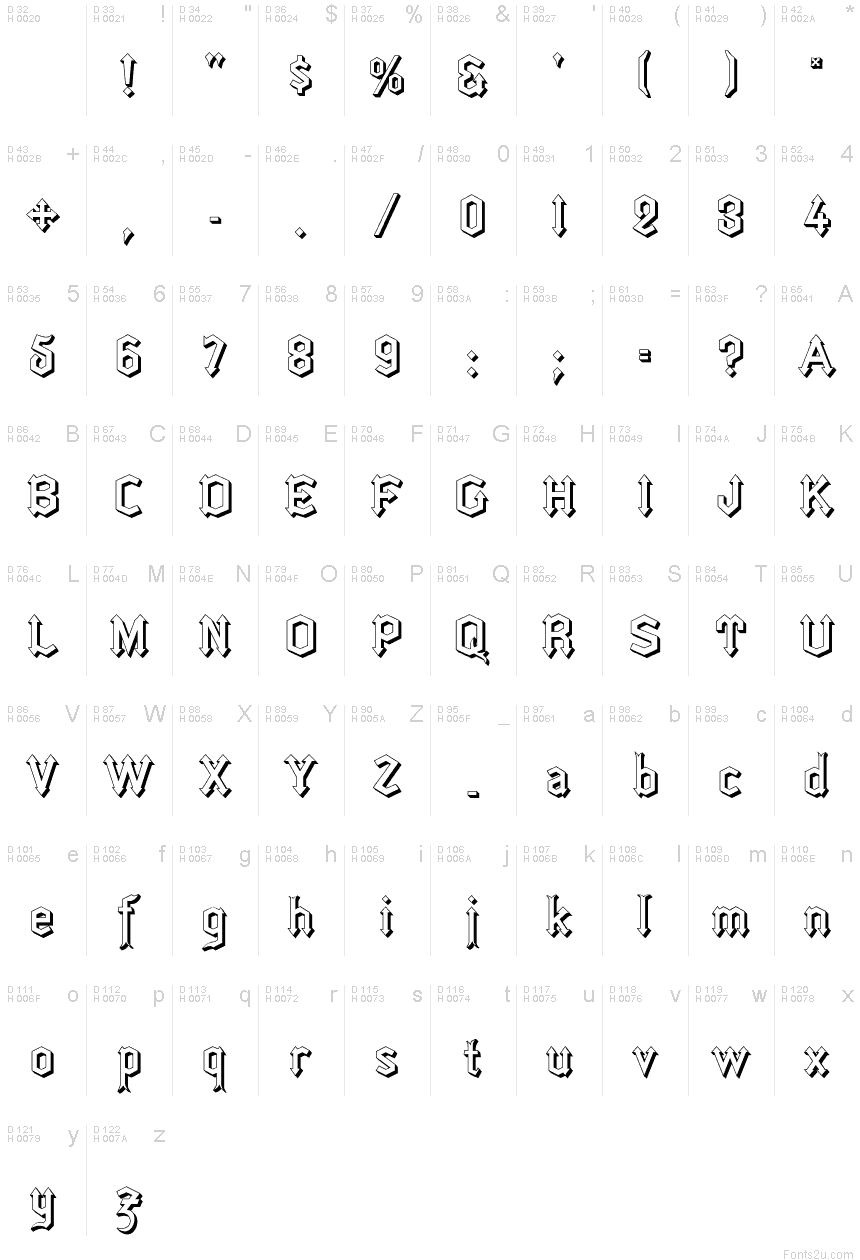
Arrowhead Lake Shadows to darmowy krój pism nagłówkowy w stylu westernowym z konturem. Jego wysokie, kanciaste litery posiadają spiczaste szeryfy klinowe i ostro cięte narożniki. Przesunięte cienie tworzą rzeźbione, przestrzenne oblicze z wyraźnym oddzieleniem.
Może nadać plakatom rodeo siłę dawnych napisów szyldowych, a zarazem jego geometryczne kontury pasują również do grafiki gier i gadżetów muzycznych. W przypadku opakowań w stylu ranczerskim i brandingu dziedzictwa kulturowego groty przypominające strzały mogą stać się częścią emblemata zamiast służyć jako neutralny tekst.